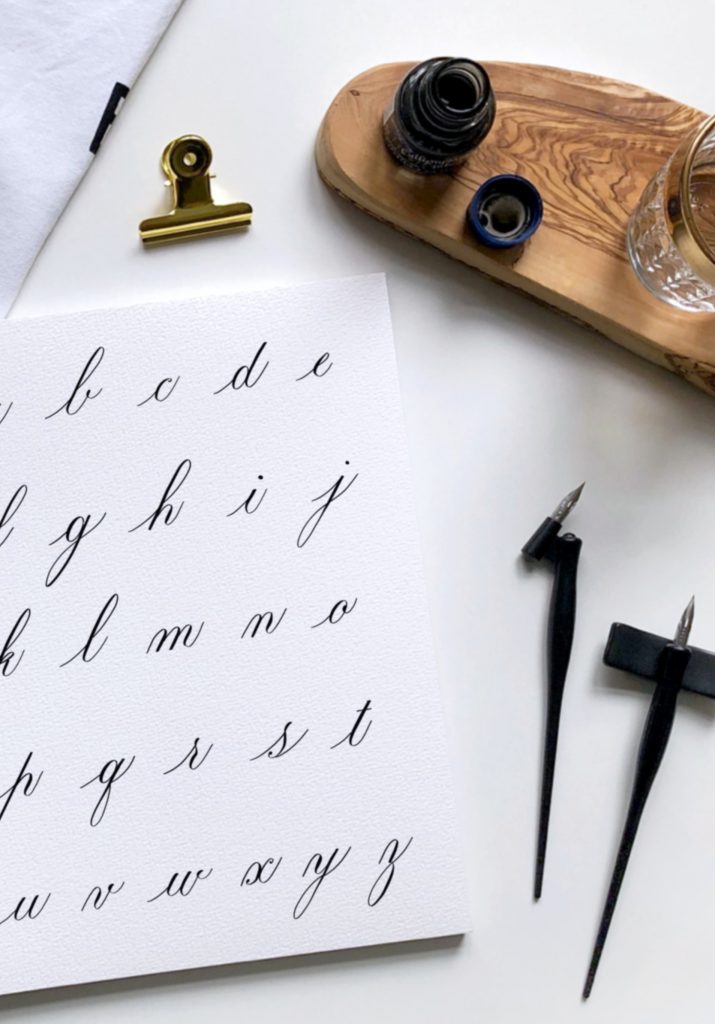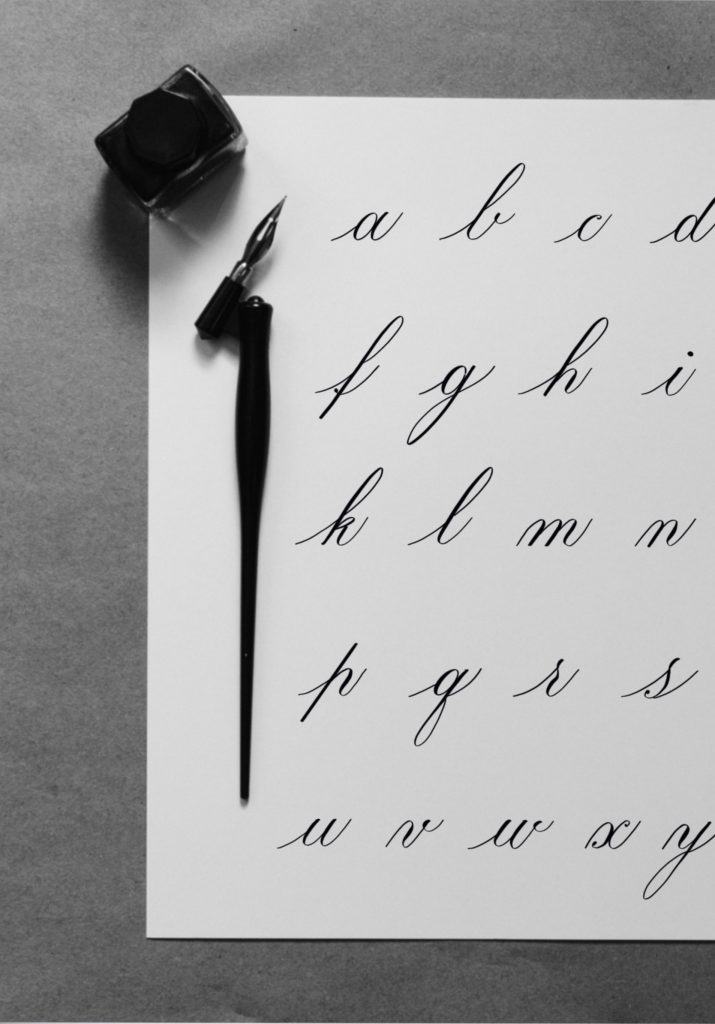
Fedezd fel magadban a művészt a kalligráfia segítségével és éld át a flow élményt!
Kalligráfia Flow munkafüzet
Üdvözöllek a 7 napos ingyenes Kalligráfia Flow kihívás nyitóoldalán! Gyakorold a tudatosságot a jelenben 7 napon keresztül – 2023. október 16. és 22. között – a kalligráfia segítségével és engedd szabadjára a benned rejlő művészt.
Fedezd fel a művészi tudatosságot!
Ez a kihívás nemcsak arról szól, hogy gyönyörű betűket tanulunk, hanem arról is, hogy megtaláld a flow-t a kalligráfia segítségével. A következő 7 napban megtanulod a Copperplate stílust; az elegáns, kifejező vonásokat, amelyek lenyűgöző betűket alkotnak. De ennél is többről lesz szó – fel fogod fedezni, hogy a töltőtoll tánca a papíron hogyan vezet tudatos – mindful – pillanatokhoz.
kalligráfia Copperplate ábécé
Készítettem egy ingyenes munkafüzetet, ami telis-tele van olyan dolgokkal, amik támogatják a fejlődésed ezen a héten és azon is túl:
• gyakorlólap az alapvonásokkal,
• teljes kisbetűs Copperplate ábécé,
• üres gyakorlólap,
• és még egy idézet is, hogy további gyakorlásra inspiráljon!
Plusz napi videók segítik a tanulást a Pearl Letters Squad Facebook csoportban, hogy még jobban el tudd sajátítani ennek a fantasztikus betűtípusnak a titkait.
Copperplate kalligráfia idézet
Találd meg a belső békédet a kalligráfiával!
A folyamatosan rohanó világban a kalligráfia menedéket kínál. A kalligráfia segít a lelassulásban, végy egy mély lélegzetet, és éld át a flow élményt minden egyes vonással! Ebben az egy hétben megtapasztalod, hogyan segít a kalligráfia elérni a tudatos jelenlétet. A kalligráfia esélyt ad, hogy nyugalmat találj a mindennapok nyüzsgésében.
kalligráfia Copperplate ábécé 2
Éld át a flow élményt!
Hallottál már a flow-ról? Ez az az állapot, ahol az idő megszűnik, és szárnyal a kreativitás. A kalligráfia segítségével átélheted ezt a varázslatos érzést. Napi 10-20 perc gyakorlással felfedezheted a saját flow pillanataidat. Mondj búcsút a stressznek, és üdvözöld a tudatosságot a jelenben, a mindfulnesst!
Fejezd ki magad a művészet segítségével!
Akár új hobbit keresel, akár egy kis stresszoldást vagy a meditáció egyedi módját, a kalligráfia a megoldás. A kihívás során nemcsak a Copperplate stílust sajátíthatod el, hanem megtapasztalhatod az önkifejezés örömét a művészi kézíráson keresztül.